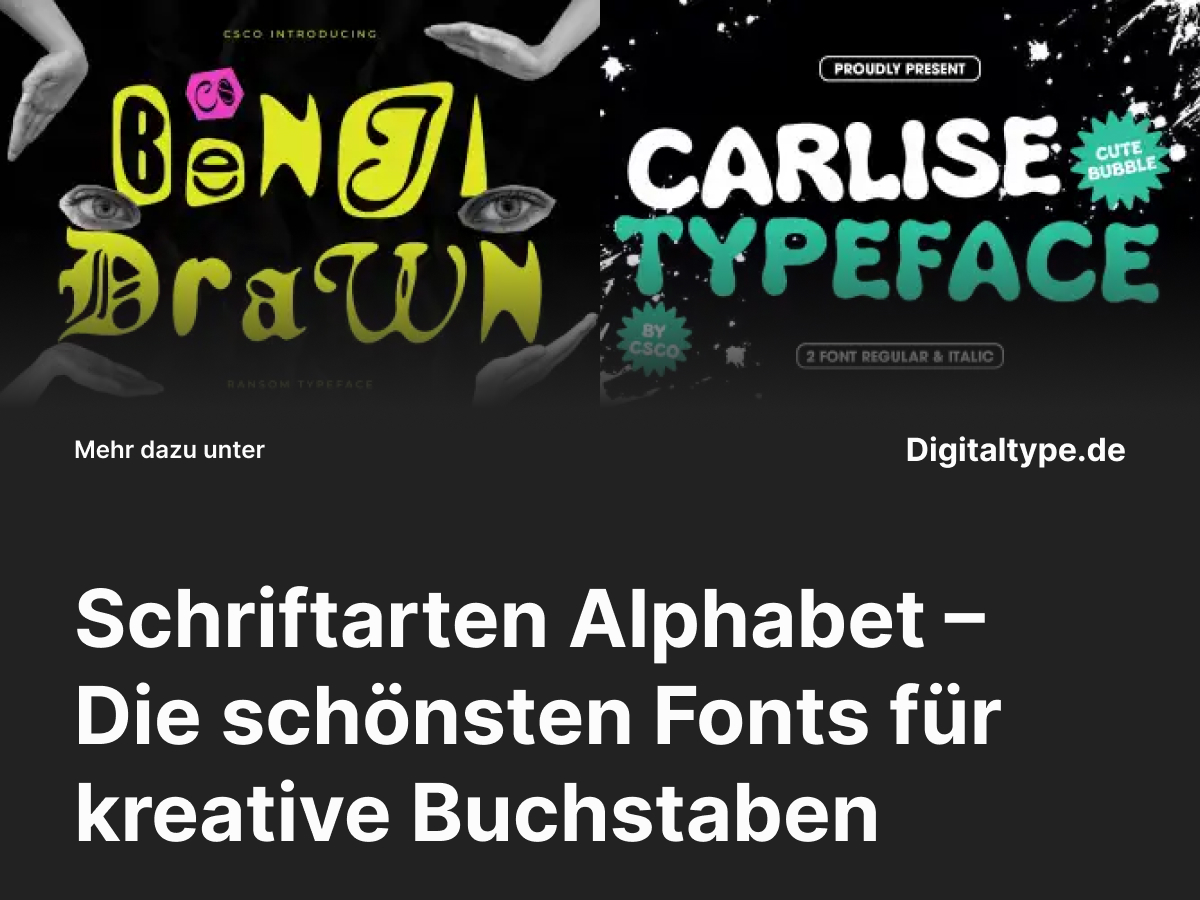
Schriftarten Alphabet – Die schönsten Fonts für kreative Buchstaben
Ob für Poster, Logos, Kinderbücher oder digitale Designs – eine Schriftarten Alphabet verleiht deinem Projekt Charakter und Einzigartigkeit.
In diesem Artikel stellen wir dir eine Auswahl moderner und kreativer Alphabet-Fonts vor, die von handgezeichnet bis elegant reichen und jedem Design Persönlichkeit verleihen.
Was sind Schriftarten für das Alphabet?
Unter einer Schriftarten Alphabet versteht man Fonts, die das gesamte Alphabet in besonders kreativer oder dekorativer Form darstellen. Diese Schriftarten eignen sich perfekt für Designs, bei denen Buchstaben nicht nur lesbar, sondern auch gestalterisch im Mittelpunkt stehen sollen.
Sie werden häufig in Branding, Kinderprojekten, Plakaten oder Einladungen verwendet, um Emotionen, Stil oder Verspieltheit auszudrücken.
Designer schätzen Alphabet-Schriften, weil sie das Zusammenspiel von Buchstaben und Formen zelebrieren – ideal für kreative Layouts mit Charakter.
Wann du eine Alphabet-Schriftart verwenden solltest
• 1. Für Kinderdesigns und Lernmaterialien: Ideal für Projekte, die Spaß und Verspieltheit vermitteln sollen.
• 2. Für Logos und Branding: Wenn du mit individuellen Buchstabenformen einen einzigartigen Markenauftritt schaffen willst.
• 3. Für kreative Social-Media-Posts: Alphabet-Schriften ziehen Aufmerksamkeit auf sich und betonen kreative Aussagen.
• 4. Für Poster und Einladungen: Besonders geeignet, wenn Typografie zum visuellen Highlight werden soll.
Eine Schriftarten Alphabet ist die perfekte Wahl, wenn du Typografie als gestalterisches Element einsetzen möchtest – verspielt, edel oder handgezeichnet.
Die 6 besten Schriftarten Alphabet für moderne Designs
Hier findest du sechs exklusive Schriftarten Alphabet, die durch ihre Einzigartigkeit, Vielseitigkeit und kreative Ausdruckskraft überzeugen. Perfekt für Branding, Kinderdesigns, Plakate oder künstlerische Projekte.
1. CS Benji Drawn Font
CS Benji ist ein handgezeichneter Alphabet-Font mit charmanten Details. Ideal für kreative Projekte, Illustrationen und persönliche Designs, die Authentizität ausstrahlen.
2. Carlise Cute Font for Kids
Carlise ist eine verspielte Kinderschrift mit weichen Linien und klaren Buchstaben. Perfekt für Lernmaterialien, Kinderbücher oder Branding mit freundlichem Charakter.
3. CS Juicy Color Font Outline
CS Juicy Color bringt Farbe und Spaß ins Design. Mit ihrem Outline-Stil eignet sie sich hervorragend für Poster, Pop-Art-Designs oder kreative Typografieexperimente.
4. Lucylane Signature Typeface
Lucylane ist eine elegante Handschrift mit fließenden Formen. Ihre Buchstaben verleihen jedem Text Stil und Persönlichkeit – ideal für Einladungen, Mode und Branding.
5. Gamour Elegant Serif Font + Bonus
Gamour ist eine elegante Serifenschrift mit feiner Balance und klaren Linien. Perfekt für edle Layouts, Editorials oder Branding-Projekte, die Stil und Klasse vermitteln sollen.
6. Rovey Handwritten Serif Font + Bonus
Rovey kombiniert handschriftlichen Charme mit klassischer Serif-Struktur. Ihre einzigartigen Buchstaben machen sie zur perfekten Wahl für kreative und emotionale Designs.
Design-Tipps für Alphabet-Schriftarten
• 1. Wähle Fonts passend zur Stimmung: Verspielt für Kinderprojekte, elegant für Branding, markant für Poster.
• 2. Experimentiere mit Farben: Alphabet-Fonts wirken besonders stark mit farbigen Buchstaben oder Texturen.
• 3. Kombiniere verschiedene Stile: Eine Mischung aus Serif und Script kann interessante Kontraste schaffen.
• 4. Achte auf Lesbarkeit: Besonders bei dekorativen Alphabet-Fonts sollte der Text verständlich bleiben.
Fazit: Schriftarten Alphabet für kreative Gestaltung
Eine Schriftarten Alphabet ist weit mehr als nur Text – sie ist ein Gestaltungselement, das Emotionen, Stil und Kreativität vermittelt.
Die Wahl des richtigen Fonts kann deinem Design Leben einhauchen, ob verspielt, elegant oder handgezeichnet.
Die vorgestellten Fonts zeigen, wie vielfältig Alphabet-Schriften eingesetzt werden können – perfekt für Designer, die Buchstaben in Szene setzen wollen.